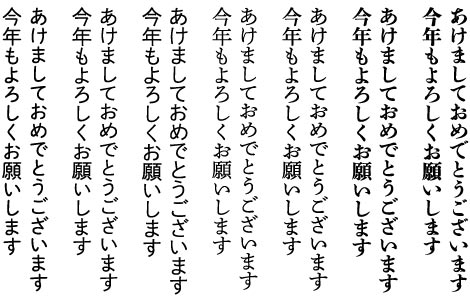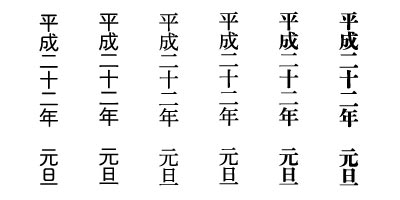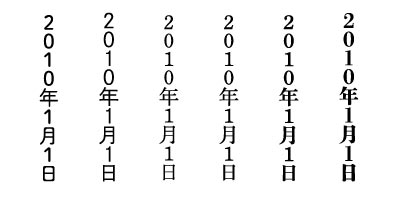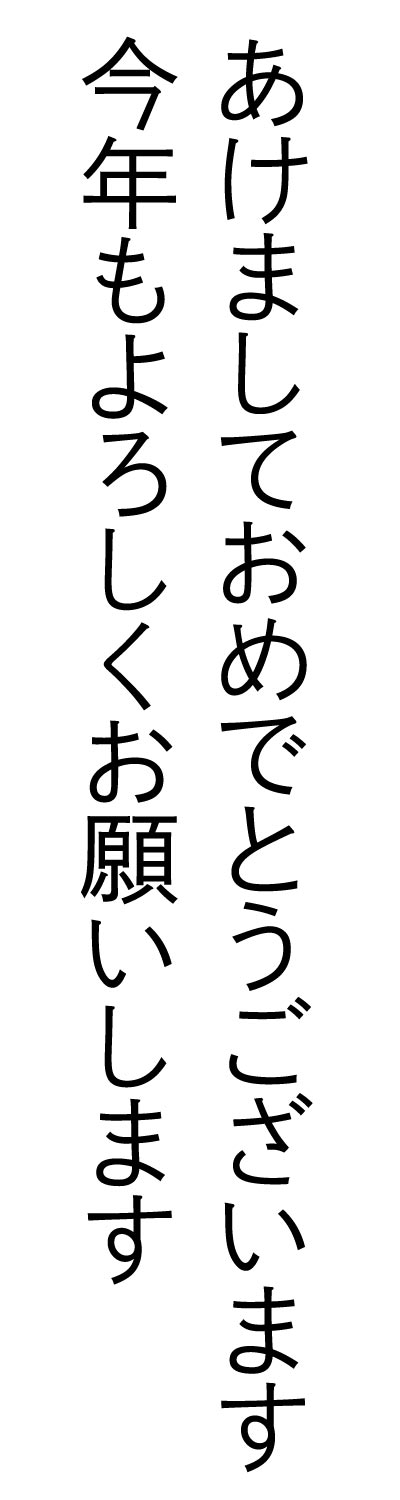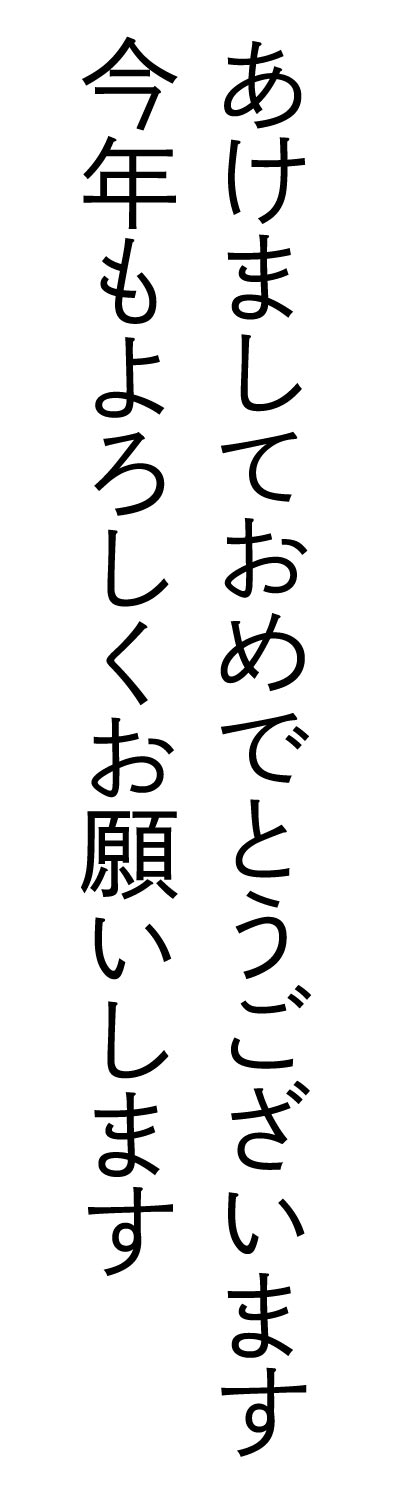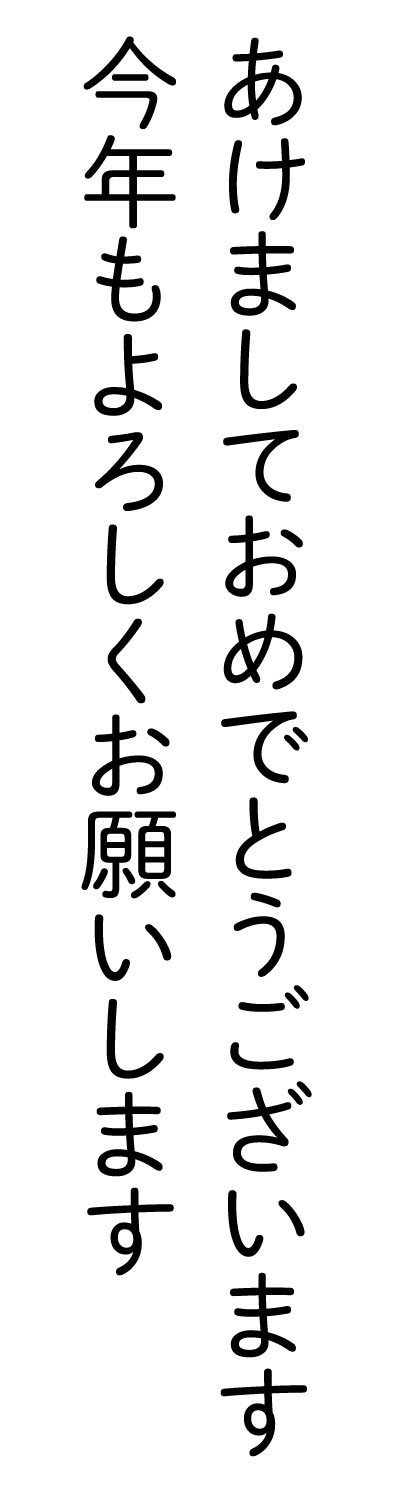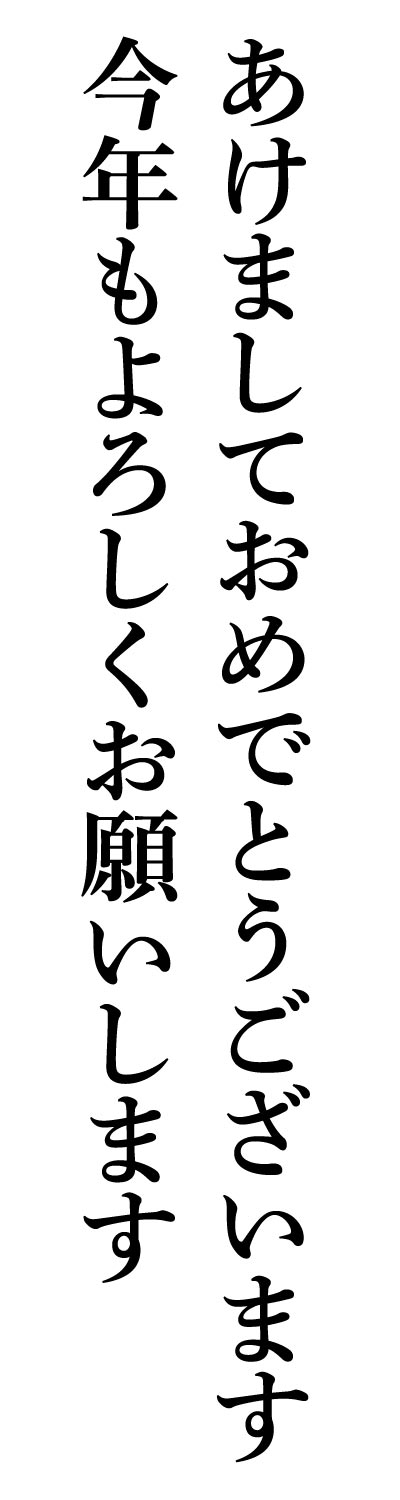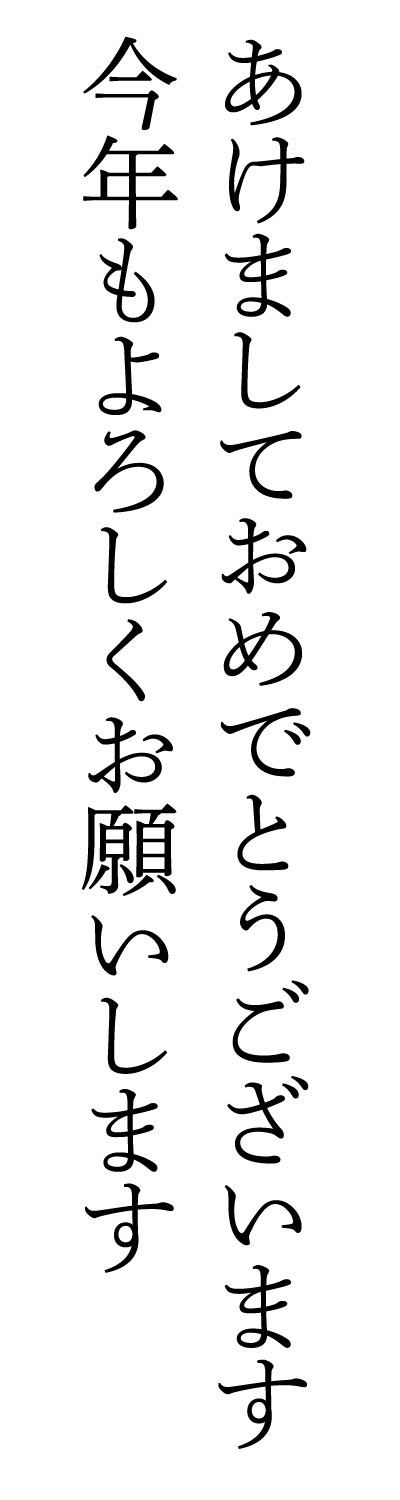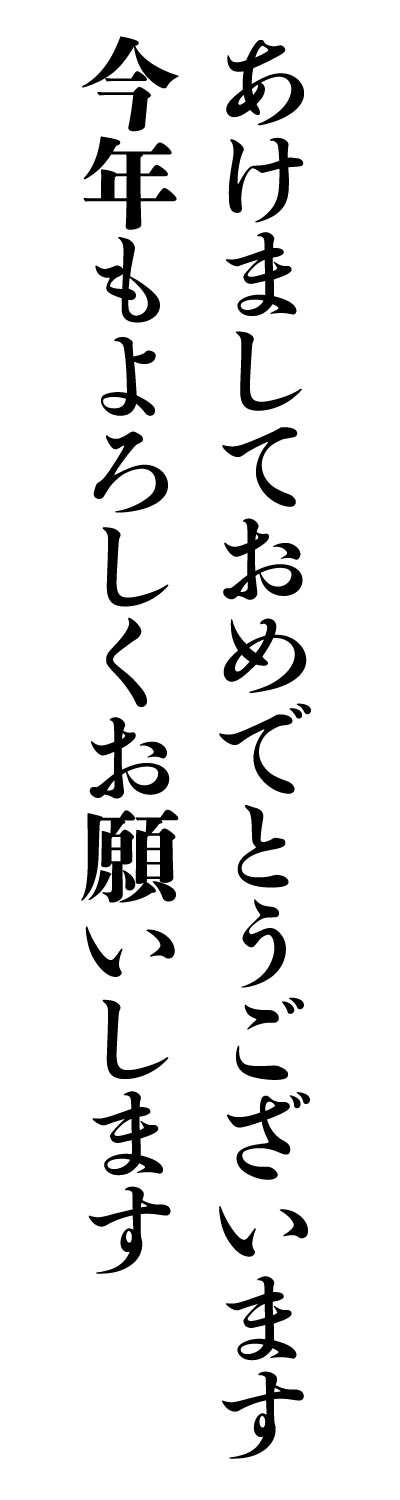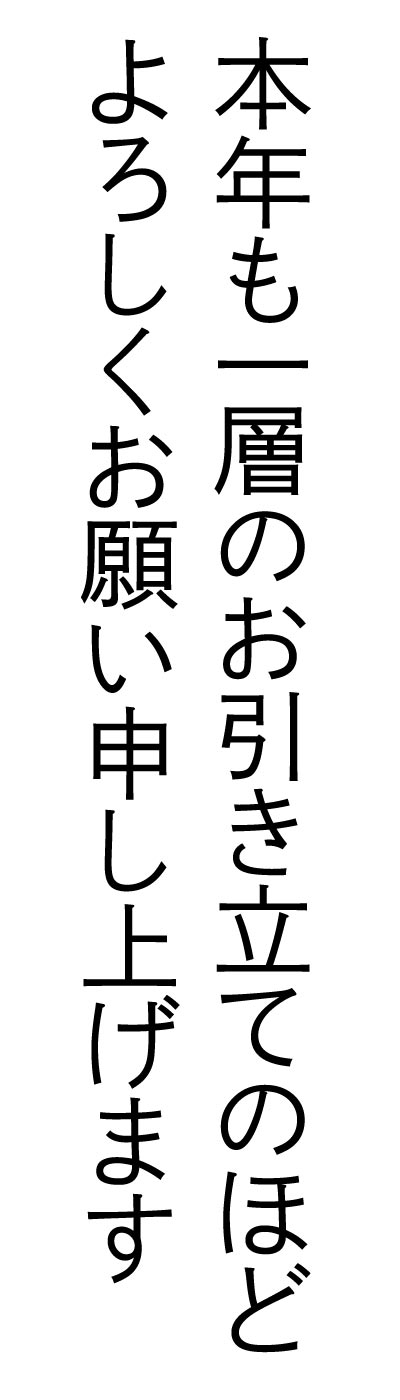
第30回 2009年は新しい秀英体で年賀状を作ろう!
元旦に年賀状を届けるには25日まで! と思いながらも例年通りのみなさま、今年も秀英体で年賀状はいかがでしょうか。
今回の秀英体のコネタは、一年間のご愛顧に感謝いたしまして、見本帳……ではなく、リニューアルしている秀英体で年賀状文例をご用意しました。
11月からMORISAWA PASSPORTで提供開始になった秀英明朝L(秀英細明朝体)だけでなく、来年度提供予定の秀英明朝M・B、そして皆さんお待ちかねの秀英初号明朝。また、秀英体の新たな利用シーンを広げるべく目下開発奮闘中の秀英角ゴシック&丸ゴシックも大放出!
定番のご挨拶
改刻秀英体のオールキャストを一列に並べてみました! Gメン'75みたいですね!
右から
年賀状では、明朝体よりも筆書体が一般的です。しかし秀英初号明朝の仮名は筆の勢いが強く残っているデザインですし、漢字も堂々として、年賀状でも違和感がありません。
秀英明朝L・M・Bのファミリーは、太さが異なります。文字の大きさや、ご家庭のプリンターの性能に合わせて、ちょうど良い太さを選んでいただけます。
角ゴシックは仮名が2種類あります。まだ開発中のため、仮に「A」「B」と呼んでいます。Aのほうは、既存の秀英ゴシックを継承した、オーソドックスな角ゴシック体。Bのほうは、秀英明朝Lの骨格を使い、文字が持つうねりを生かしたちょっぴり個性的な角ゴシック体です。
また、丸ゴシックは、本文組版もできそうな、小ぶりで温かみのあるデザインです。どことなく懐かしい雰囲気です。
いずれもこれから仮名・漢字ともさらにブラッシュアップしていく予定です。
目上の方へのご挨拶
上司、先生など目上の方へのご挨拶向けの、丁寧な文例です。
謹んで新春のご挨拶を申し上げます
旧年中はお世話になりありがとうございました
本年もご指導、ご鞭撻のほどよろしくお願い申し上げます
お得意先へのご挨拶
一年間、がっちりと組んで汗を流したビジネス上のお相手へ、しっかりした文例です。
謹んで新年のお慶びを申し上げます
旧年中は格別のご愛顧を賜りありがとうございました
本年も一層のお引き立てのほどよろしくお願い申し上げます
来年の干支は……寅!
来年の干支は「寅」ですので、この一文字をバーンと大きく使いたいですよね。
個性様々な秀英体ファミリーを試して、お気に入りの「寅」を見つけてください。
※角ゴシックA・Bは、漢字は共通のデザインですので1種類です。
上段右から
下段右から
忘れちゃいけない、元旦!
もちろん日付も抜かりなく秀英体です。来年は平成22年、2010年です。
※角ゴシックA・Bは、漢字・数字は共通のデザインですので1種類です。
右から
最後にちょっとアピールしてもいいですか……?
あっという間の2009年、さまざまなかたちで秀英体をご紹介することができました。
ついについについに、第一弾として秀英明朝LをMORISAWA
PASSPORTを通じて、皆様にお届けすることができました。長いようであっという間!
そして来年には、ファミリーの秀英明朝M・B、秀英体のフラッグシップである秀英初号明朝を、なんとしてもリリースできるよう、開発メンバー一同、目の下にクマを作りながらがんばっております。楽しみにお待ち下さい。
Flash見本帳が誕生したり、新しい取り組みが少しずつ実ってきた年でもありました。
来年も、秀英体の取組みをご紹介してまいります。変わらないようで変わっていく秀英体を、2010年もよろしくお願い致します。
よいお年を!